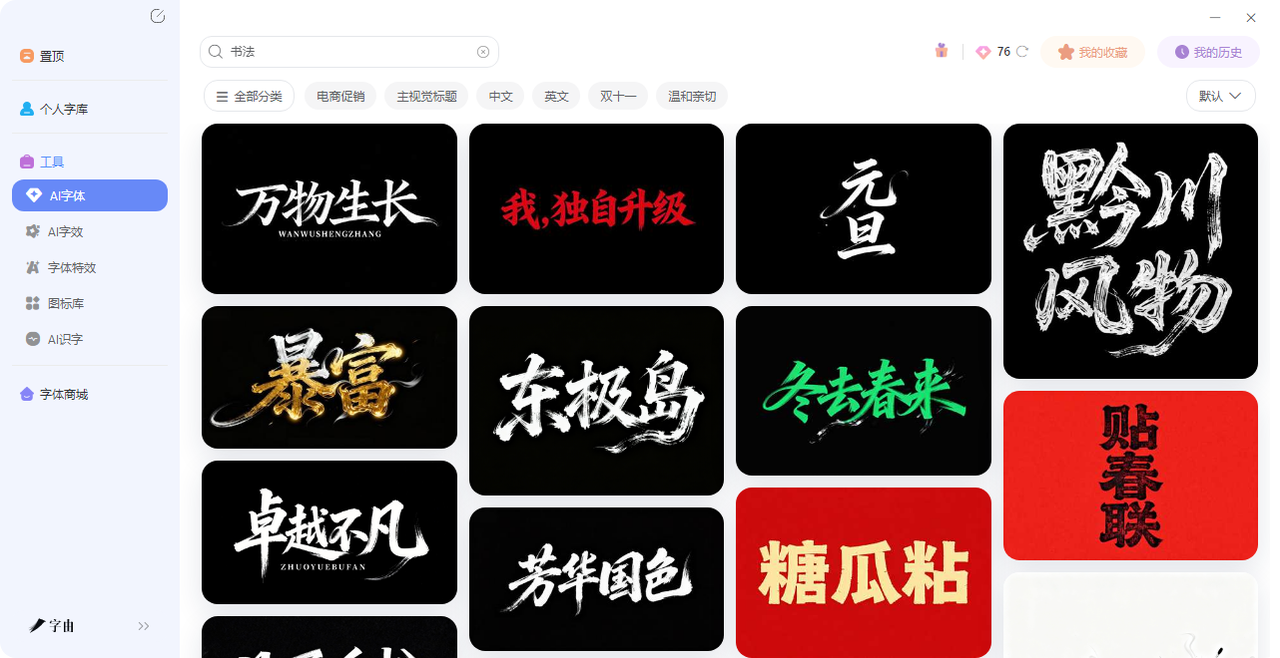
还在手写行楷?试试行楷字体转换器,字由3秒出效果图
以前想要一款好的楷书字体可能要四处寻找字体作为参考,又或者是直接找人来花钱设计,但是现在这些烦恼可以统统被解决掉了,今天就说一个工具:字由。这里一共有两个方法。第一个是用AI字体,输入文字直接生成行楷效果图,几十秒出图。第二个是激活行楷字体库,让PS和Word里多出一批可编辑的行楷字体,不用下载安装。不过不论是哪一个选择都十分方便。接下来我会详细介绍。
2、第一个方法:AI字体——行楷效果一键生成,几十秒出图
- 在搜索框里输“书法”,字由会把相关的模板列出来。第二,在左边的分类栏里找“国潮风”或者“书法风”,这两个分类下面藏着不少行楷风格的模板,在AI字体里能找到气质很接近的模板。
- 找到喜欢的模板之后,点一下模板卡片。这时候会进入编辑界面,你会看到一个默认的文字,比如“字由”或者“书法”。把它删掉,换成你自己的文案。做标题的话,字数不要太长,四五个字最合适。比如“海纳百川”“厚德载物”“春华秋实”。
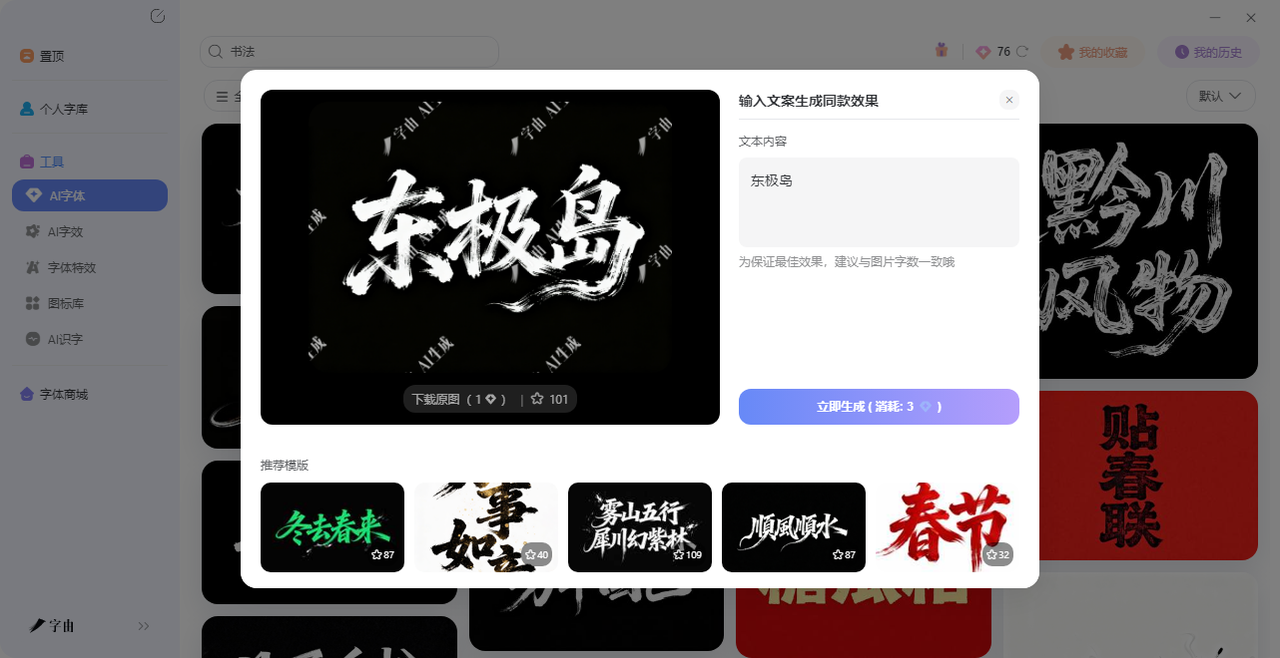
- 改完文字之后点“生成”。字由的AI会开始渲染,这个过程大概20到30秒。具体时长看你输入的字数和服务器当时的负载,但一般不会超过一分钟。生成之后你会看到一张高清的图片,背景是透明的,可以直接下载PNG格式。
3、行楷字体库——激活后随时调用,文字可编辑
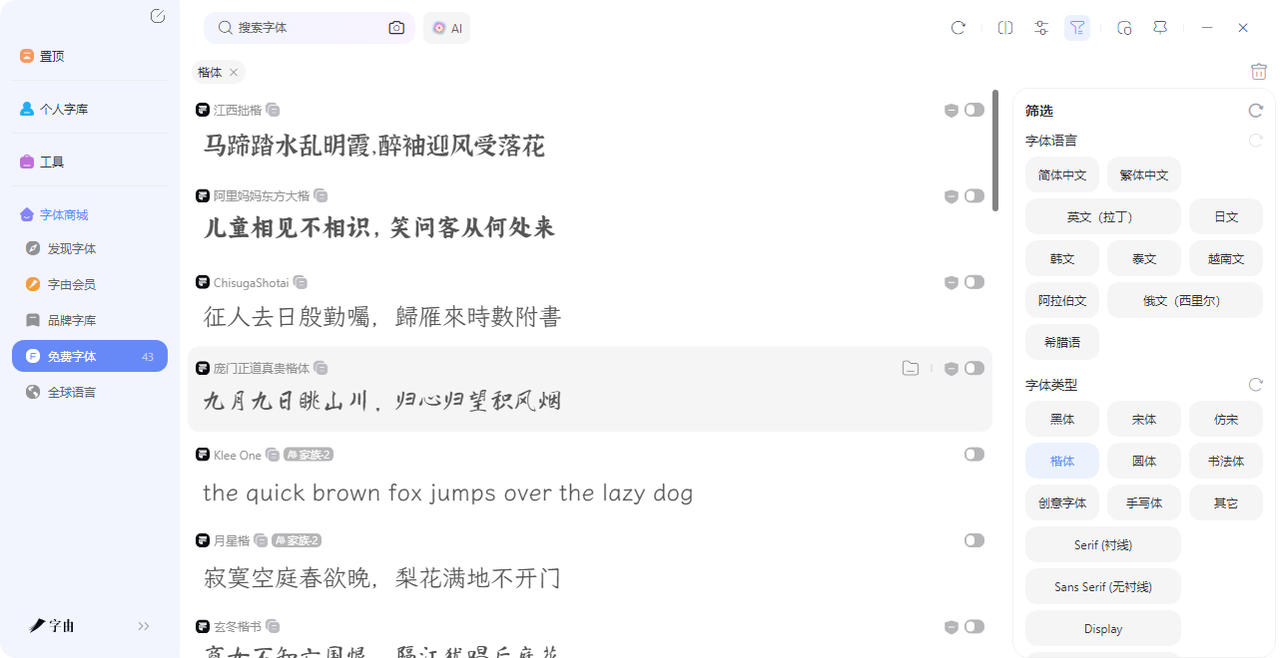
- 江西拙楷。这款字体很有意思,它不是那种工工整整的楷体,而是带一点“拙”的感觉。笔画不追求绝对的平滑,反而保留了一些手写的生涩感。做国风标题、复古包装、文创产品的时候用这款,味道特别对。
- 阿里妈妈东方大楷。阿里官方出品的免费字体,骨架非常严谨,笔力雄厚。适合做大尺寸的标题,比如电商海报、品牌主视觉。这款字体的字形偏方正,稳重但不呆板。
- 三极行楷简体。名字就告诉你了,它是行书和楷书的结合体。比楷书流畅,比行书克制,是标准的行楷写法。做邀请函、画册标题、书籍封面都很合适。
- 月星楷和寒蝉活仿楷。这两款相对小众一些,但也有自己的特色。月星楷偏秀气,适合女性向或者文艺风的设计;寒蝉活仿楷带一点古朴感,适合做旧风格的物料。